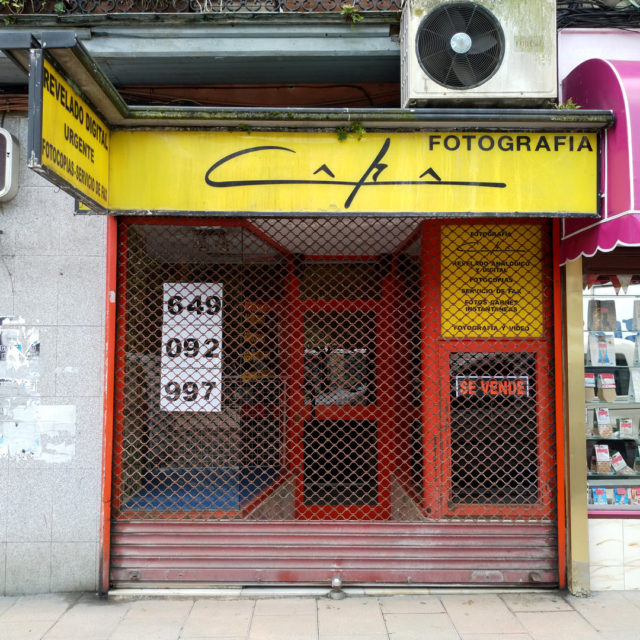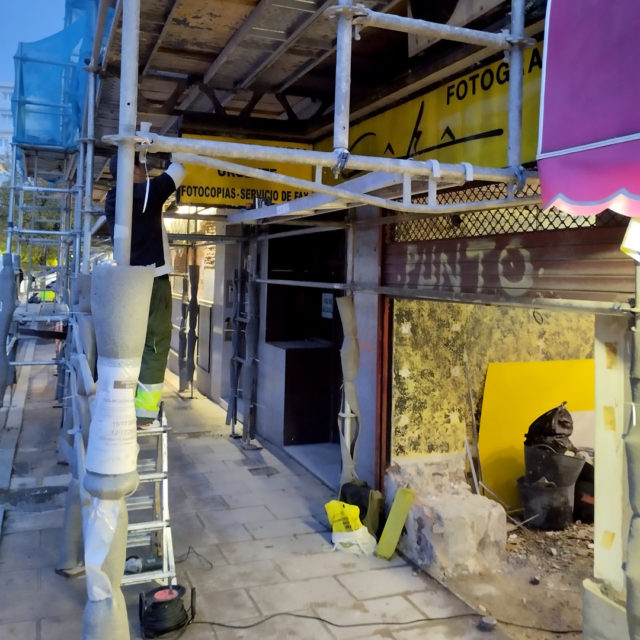
Fotografia Capa
La semana pasada nos avisaron de que ya habían comenzado las obras en el local de esta tienda de fotografía que llevaba cerrada varios años. El actual propietario, nos llamó para ver si queríamos recoger los carteles y rótulo principal de la tienda. El viernes pudimos bajarlos y ahora quedan preservados junto al resto de rótulos que vamos salvando.
De la imagen, destaca el uso de la tipografía manuscrita, que podemos entender era la del `antiguo propietario y fundador. Sobre «Fotografía Capa» no disponemos de muchos datos, por lo que nos gustaría pedir la colaboración de todos, para poder conocer la historia de este comercio, que como vemos ya apenas quedan en nuestras calles.